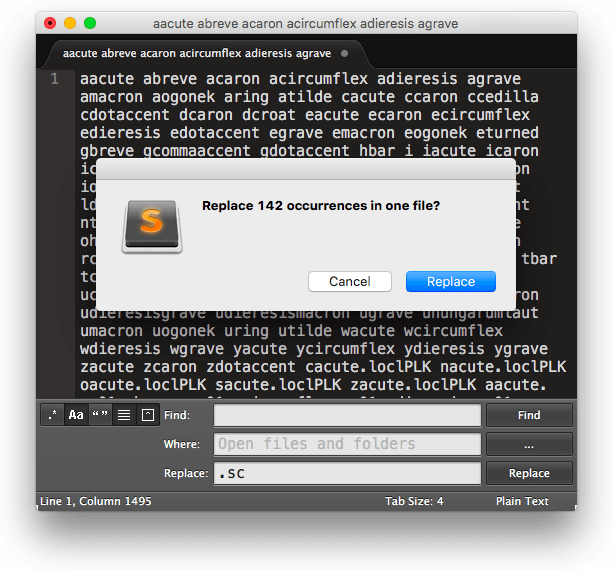
さて、すべての大文字グリフを終え、波に乗っていますか?ここでは、ソフトウェアが大文字からスモールキャップを生成する方法を紹介します。
複製とリネーム
Glyphsは、スモールキャップに特別な命名規則を採用しています。小文字の名前に接尾辞.scを付けます。あるいは、小文字からスモールキャップへの変換には.smcp、大文字からスモールキャップへの変換には.c2scという接尾辞もあります。
まず、スモールキャップにしたいすべての文字を複製する必要があります。一般的には、コンポーネントで構成されていないすべての大文字が対象となります。フォントビューの左下にある歯車のアイコンをクリックし、「スマートフィルタを追加」を選択することで、これらを簡単にフィルタリングできます。次に、「パスの数」、「より大きい」、「0」を選択します。
さて、Cmdキーを押しながら選択することで、フィルタと「文字 > 大文字」を同時に選択します。これにより、コンポーネントを持たないすべての大文字が得られます。
もしデザイン上必要なら、数字、句読点、記号のスモールキャップのバリエーションも忘れないでください。この例では、大文字に絞ります。選択したすべての文字を選び、「グリフ > グリフを複製」(Cmd-D)に進みます。これで、複製されたすべてのグリフに.001という接尾辞が付きます。
さて、スモールキャップには.scという接尾辞が付くので、リネームする必要があります。しかし、一つずつリネームする必要はありません。.001グリフをすべて選択し、Shift-Cmd-Fを押すか、「編集 > 検索 > 検索と置換」に進みます。「検索」ボックスに.001を、「置換」ボックスに.scを入力し、「置換」を押します。
グリフの名前を大文字から小文字に簡単に切り替えるには、mekkablueのスクリプトの「Glyph Names」フォルダにある「Make glyph names lowercase」スクリプトを使用するだけです(Glyphs 3の場合、ここをクリックしてプラグインマネージャ経由で直接インストールできます)。これにより、選択したグリフの名前が自動的に小文字に変わります。
あるいは、マニア向けには、もっとクールな内蔵の方法があります。この小さなトリックを使えば、リネームのステップ(接尾辞の追加と小文字化)を一度に行うことができます。
繰り返しになりますが、グリフを選択し、「編集 > 検索 > 検索と置換」(Shift-Cmd-F)に進み、「検索」フィールドに(.*)\.001と入力します。(.*)は任意の数の任意の文字を意味し、\.001はリテラルのドットに続く「001」を意味します。次に、「置換」フィールドに\L\1.scと入力します。\Lは続くものをすべて小文字に変換し、\1は括弧内の最初の式、この場合は(.*)を表します。そして.scは私たちが好むスモールキャップの名前の接尾辞です。今回は、「Regex」もチェックする必要があります。これは正規表現を意味し、これらの面白いドット、アスタリスク、括弧が何かを意味するものです。超簡単!
スケーリングと微調整
さて、小さくなければスモールキャップとは言えません。したがって、グリフを「スケール」する必要がありますが、同時にステムの幅はそのままに保つ必要があります。繰り返しになりますが、これをすべて手動で行う必要はありません。ウェイト軸に複数のマスターがある場合は、Tim Ahrens氏のFont Remix Toolsの「RMX Scaler」機能を使用できます。しかし、これらは実際には単なるスケーリング以上のことをします。「RMX Scaler」はステムの幅を維持しようとします。これはスモールキャップで私たちが望むことです。しかし、RMXはあなたのステム幅を推測することはできないので、「フォント情報 > マスター」(Cmd-I)で各マスターの水平および垂直ステム幅を定義する必要があります。
次に、フォントビューまたは編集ビューで、将来のスモールキャップグリフを選択し、「フィルタ > RMX Scaler」を実行し、あなたのデザインにとって意味のある値を入力します。
各列は1つのマスターを表します。列にカーソルを置くと、RMX Scalerは編集ビューをそれぞれのマスターに切り替えるので、常に行っていることの良いプレビューが得られます。「幅」の値は「高さ」の値より高くしたいと思うでしょうし、スモールキャップの高さはエックスハイトより少し上にしたいでしょう。アウトラインを拡大する単位値を指定することで、ステムの「ウェイト」を変更することもできます。これは、スモールキャップがスペクトルの端で時々起こるように、細すぎるように見える場合です。通常、スモールキャップはもう少しスペーシングも必要です。「スペーシングを調整」フィールドに単位値を入力します。「垂直シフト」フィールドは上付きグリフ用なので、ここでは無視できます。
RMXは大きな助けになりますが、一度に非常に多くのことをこなしてくれる一方で、完成したスモールキャップを与えてくれるわけではないことを覚えておいてください。手動での微調整はまだ必要になります。
さて、これまでに達成したことはこちらです。
スモールキャップの高さ
メトリクスにはエックスハイトとキャップハイトがあるので、スモールキャップの高さもあるべきです。これを行うには、使用しているGlyphsのバージョンに応じて異なる方法があります。
Glyphs 3でスモールキャップの高さを追加する
「フォント情報 > マスター > メトリクス」に進み、「メトリクス」の見出しの隣にあるプラスボタンをクリックして、新しいメトリクスエントリを追加します。
ダイアログシートが表示され、必要なすべての情報を尋ねられます。「メトリックタイプ」として「x-Height」を選択してください。なぜなら、私たちのスモールキャップの高さは、スモールキャップグリフのエックスハイトを置き換えることになっているからです。
「名前」は任意です。私は「smallcaps」を選びました。好きなものを選んでください。そして最も重要なのは、「適用範囲」で、どのグリフにメトリクスを表示するかを決定することです。この場合は簡単です。「適用範囲」を、「ケース」が「スモールキャップ」であるすべてのグリフに設定します。
したがって、すべて正しく行っていれば、あなたのメトリクスセクションには、スモールキャップ用の新しいエントリも表示されるはずです。
メトリックエントリは、すべてのマスターで自動的に同期されます。しかし、まだ行う必要があるのは、値、つまりフォントユニットでの実際の高さを設定することです。通常、これはエックスハイトより少し上になります。この例では、エックスハイト480より50ユニット高い530を選びます。
Glyphs 2でスモールキャップの高さを追加する
「フォント情報 > マスター」に進み、新しい「カスタムパラメータ」を追加し、各マスターで「smallCapHeight」を選択します。「値」には、スモールキャップに対応する高さを入力します。この方法なら、編集ビューを何十ものガイドで散らかす必要がありません。最後に、オーバーシュートを忘れないでください。「アラインメントゾーン」の更新ボタンを押して必要に応じて調整するか、プラスボタンで手動で追加します。
अब、.scグリフを編集するたびに、編集ビューのエックスハイトの代わりにスモールキャップの高さが表示されます。
欠けているスモールキャップを追加する
他のすべての文字はどうでしょうか?簡単です。Glyphsは、まだ対応するスモールキャップがないすべての文字を追跡しています。フォントビュー(Cmd-Opt-1)に進み、左のサイドバーに「カテゴリ > 文字 > スモールキャップ」があり、まだ欠けているスモールキャップの文字数を示す動的なカウンターが表示されます。
このスクリーンショットでは、169個の潜在的なスモールキャップがあり、そのうち0個が現在フォントにあります。エントリを右クリックし、提案されたすべてのスモールキャップを選択し、「生成」をクリックします。
これは動的なカウンターであることを覚えておいてください。したがって、後で大文字または小文字を追加した場合は、スモールキャップの数を確認するようにしてください。
OpenTypeフィーチャー
スモールキャップのフィーチャーを追加するには、「ファイル > フォント情報 > フィーチャー」に進み、「更新」をクリックし、次に「コンパイル」をクリックします。これで、smcpとc2scという2つの追加フィーチャーがあるはずです。最初のsmcpは、小文字のグリフをスモールキャップに変え、c2sc(「caps to small caps」の略)は、大文字で同じことをします。
InDesign、QuarkXPress、Affinity DesignerなどのDTPアプリケーションは、通常、スモールキャップに関して2つの選択肢を提供します。
- 小文字のみをスモールキャップにする:
smcpのみをトリガーします。 - すべて(大文字と小文字)の文字をスモールキャップにする:
smcpとc2scの両方をトリガーします。
もし独自のカスタムフィーチャーコードを書く必要があり、c2scに入れるかsmcpに入れるかを決めなければならない場合は、このことを覚えておいてください。
そして、この大変な作業の後、それが実際に機能するかどうか知りたくなるでしょう。Adobeプログラムでフォントをテストする方法について詳しくはこちら。
特殊なケース
OK、特別な注意が必要なケースがいくつかあります。それらを見ていきましょう。
文字
idotlessとjdotlessを扱うには2つの方法があります。考えてみれば、スモールキャップのバリアントは、iとjのスモールキャップと全く同じに見えるべきです。フォントにi.scとj.scがすでにあると仮定して、「グリフ > グリフを追加…」(Cmd-Shift-G)でグリフ作成ダイアログを呼び出し、次のように入力できます。
i.sc=idotless.sc
j.sc=jdotless.sc
…そしてフィーチャーを更新すれば、完了です。
あるいは、フォントに重複したグリフがあるのを好まない人々の一人かもしれません。その場合は、「ファイル > フォント情報 > フィーチャー」に進み、2番目のsmcpフィーチャーを追加し、その自動化を無効にして、このコードを追加します。
sub idotless by i.sc;
sub jdotless by j.sc;
それは次のようになります。
合字は、スモールキャップのフィーチャーが合字のフィーチャーの前に実行されるため、問題にはならないはずです。もちろん、エンコードされた古い合字、最も顕著なのはfiとflがある場合を除いてです。それらはもはや使用されるべきではありませんが、残念ながら、一部のMacのキーボードレイアウトにはまだそれらが残っているため、フォントに追加する必要があります。その場合は、「ファイル > フォント情報 > フィーチャー」に進み、ccmpフィーチャーを更新してください。それには、少なくともこれらの2行を含むルックアップが含まれているはずです。